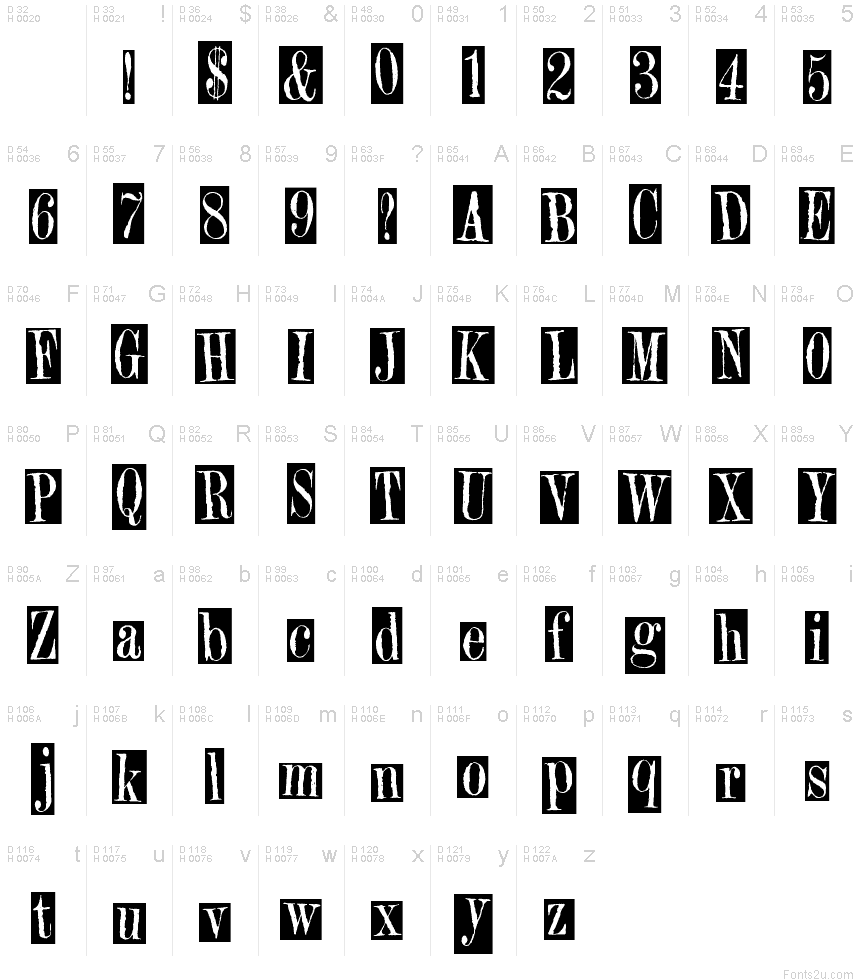
2Peas Gift autorstwa Melissy Baxter to darmowy, ozdobny krój szeryfowy o postarzanym charakterze, z nieregularnym śladem ręcznie wycinanego druku. Wysokie, wąskie litery łączą tępe szeryfy z drżącymi krawędziami i drobnymi wyszczerbieniami wzdłuż linii. Całość sprawia surowe, ręcznie robione wrażenie.
Jej zużyty, starodrukowy charakter pasuje do plakatów muzyki folkowej i grafik wydarzeń historycznych, gdzie niedoskonałe liternictwo może podkreślić klimat epoki. Sprawdza się również jako wyrazista etykieta na przetwory czy napoje rzemieślnicze. Okładki książek i ręcznie robione towary mogą wykorzystać surowe kontury jako część ilustrowanej identyfikacji wizualnej w warsztatowym stylu.